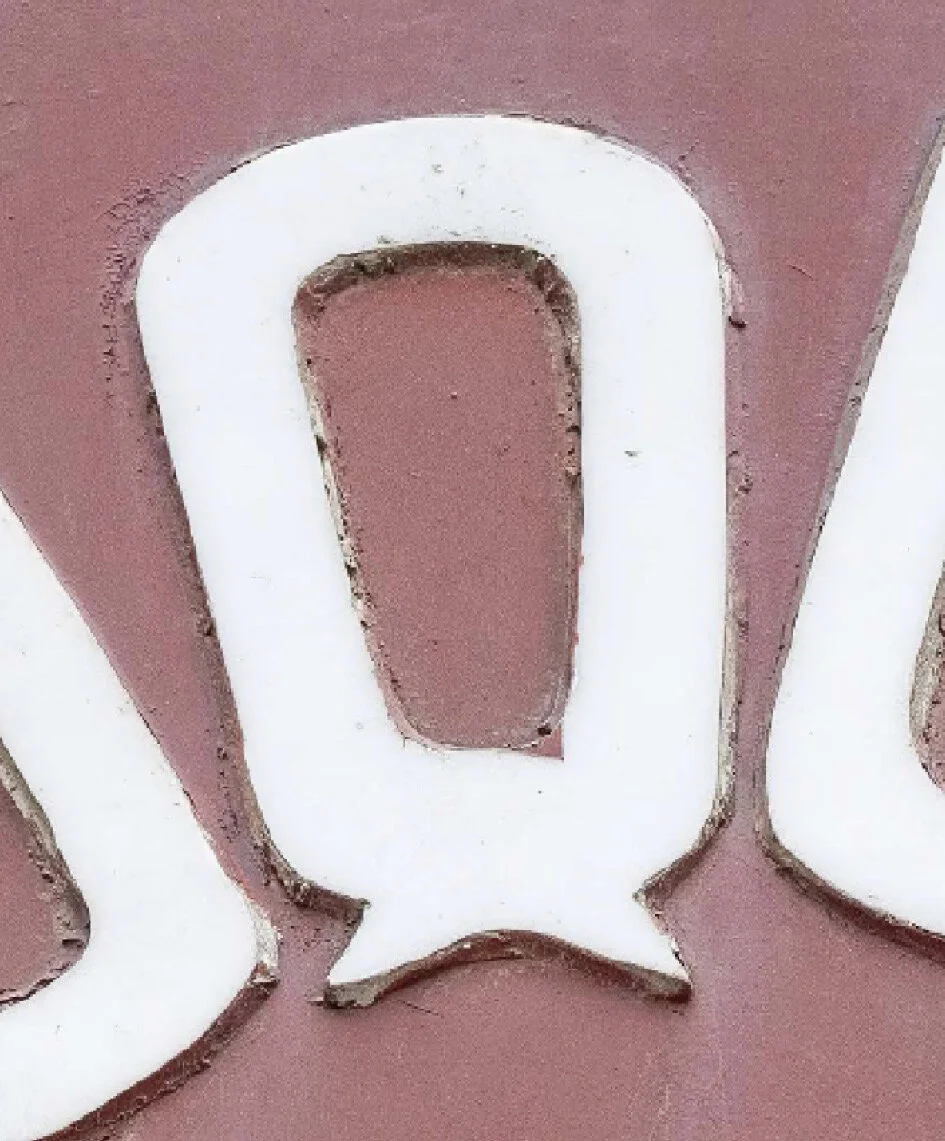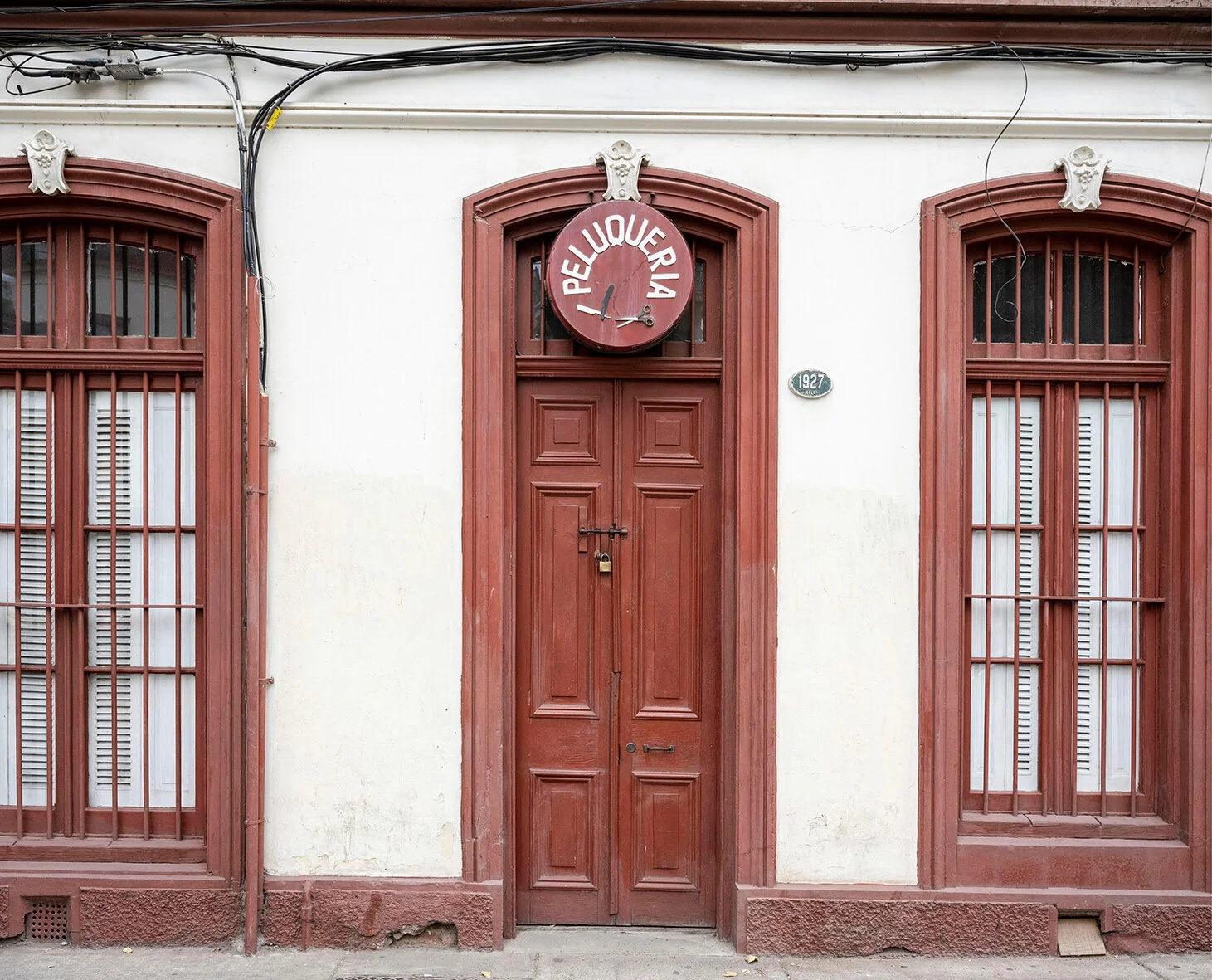
Esta peluquerΓa es de Luis Schwaiger, de padre austriaco y madre chilena. Lleva mΓ‘s de 65 aΓ±os en el rubro y cuenta que en su Γ©poca gloriosa llegaba a atender mΓ‘s de 30 personas diarias. Sus clientes eran en su mayorΓa hombres, muchos extranjeros que se hospedaban en ValparaΓso y los trabajadores de la Chiletabacos y del Hospital Van Buren. El hermoso letrero lo hizo Γ©l mismo, utilizando una sierra con la que cortΓ³ cada letra y su icΓ³nica navaja y tijera.